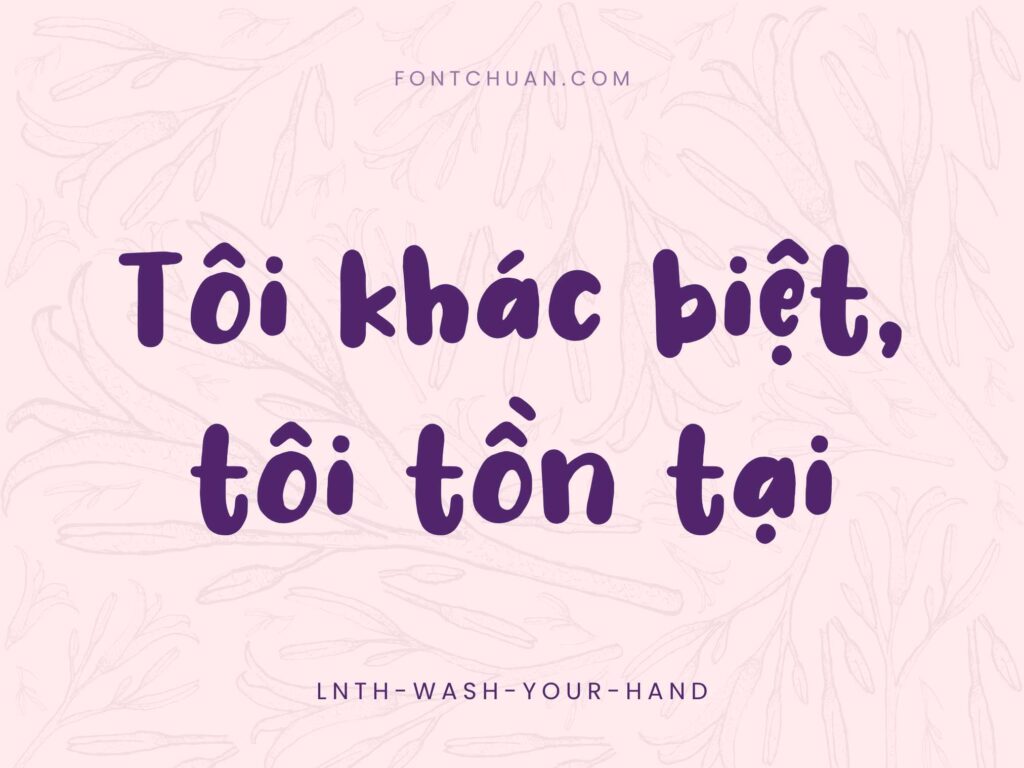
Font LNTH Wash Your Hand Việt Hóa
Tác giả Font: Khurasan
Font Wash Your Hand là một font chữ độc đáo với phong cách viết tay tự nhiên, mang lại cảm giác vui nhộn và gần gũi. Kiểu chữ này được thiết kế theo lối chữ viết tay thoải mái, không theo khuôn mẫu cứng nhắc, giúp tạo ra sự thân thiện, dễ tiếp cận và mang hơi hướng thủ công. Đây là một lựa chọn tuyệt vời cho các thiết kế giáo dục, quảng cáo, bao bì sản phẩm hoặc các ấn phẩm truyền thông cần sự sáng tạo.
Phiên bản này đã được Việt hóa bởi LNTH, hỗ trợ đầy đủ tiếng Việt cùng hơn 50 ngôn ngữ khác, giúp người dùng dễ dàng ứng dụng trong thiết kế quốc tế. Font Wash Your Hand được các thành viên Font Chuẩn sưu tầm và đăng tải nhằm mang đến một font chữ mang phong cách viết tay tự nhiên, phá cách và trẻ trung.
Về đặc điểm thiết kế, Wash Your Hand có nét chữ mềm mại, hơi nghiêng nhẹ, tạo cảm giác vui nhộn và thoải mái. Kiểu chữ này phù hợp với thiết kế tiêu đề, typography sáng tạo, quảng cáo, nhãn dán hoặc các ấn phẩm hướng đến trẻ em và giáo dục.
Font Wash Your Hand được ứng dụng rộng rãi trong các sự kiện như Thiệp cưới, Sinh nhật, Lễ hội hoặc các thiết kế hướng đến trẻ em. Nó phù hợp với nhiều ngành nghề như quảng cáo, giáo dục, in ấn sáng tạo, thiết kế sản phẩm thủ công và đồ họa vui nhộn.